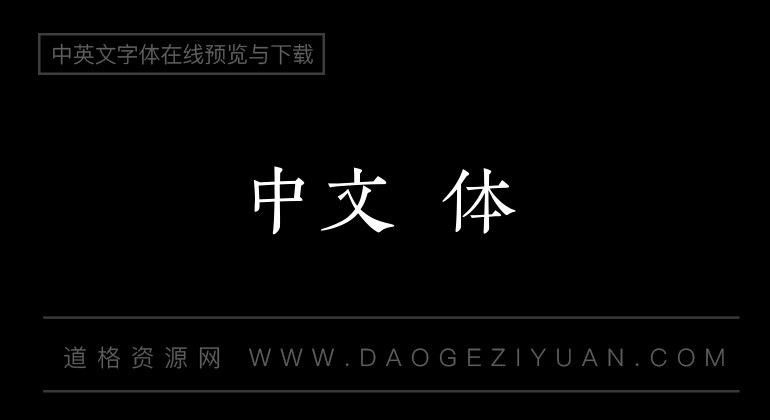
田氏金铃体演示版是一款由田氏字体设计团队开发的免费演示字体。这款字体设计精美,笔画流畅,字形清晰,有助于提高文本的可读性,是一款非常适合用于文字处理、排版等方面的字体。它具有简洁大方的风格,可以让文字更加突出,更加美观。此外,这款字体还具有抗锯齿等特性,可以让文字在显示器屏幕上更加清晰,更加精美。文件名:TianShiJinLingTiYanShiBan-1.ttf
田氏金铃体演示版是一款非常不错的手写艺术字体,具有很好的视觉感,适合于文化类的宣传设计、商业类品牌的广告和产品包装设计以及个性化文字排版等较多场景。